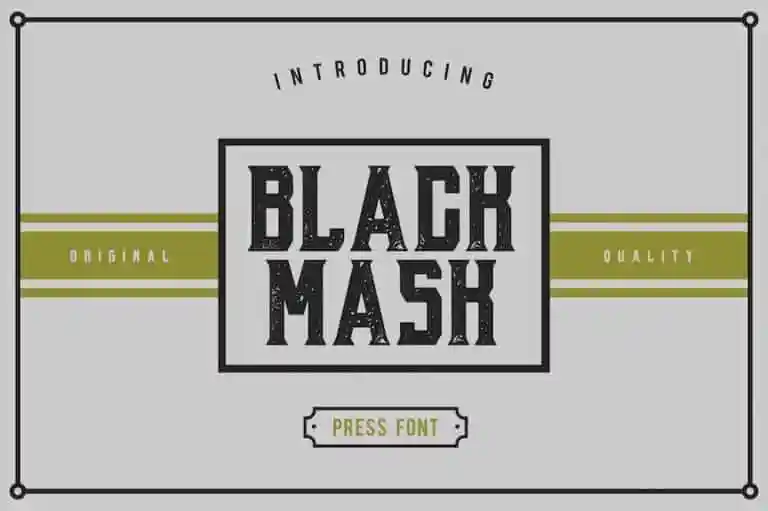
Black Mask Typeface – Download Grátis
Introduzimos uma nova tipografia chamada “Black Mask Typeface”. Esta é uma seleção de estilos inspirados na década de 1920 e 1930, repleta de sombras do tipo fantasia, scrolls vintage, painéis e ornamentos. Ideal para criar design de rótulos, headlines, logotipos, sinalização, cartazes, cartões de visita, camisetas e muito mais. Este conjunto de estilos modernamente vintage é perfeito para quem busca uma fonte de estilo retro que brilha em todas as aplicações de design. Através da combinação desses elementos, você pode criar designs únicos, repletos de personalidade e graça. Com a Black Mask Typeface, o mundo dos rótulos e logotipos ganha um toque vintage que certamente não deixará ninguém indiferente.